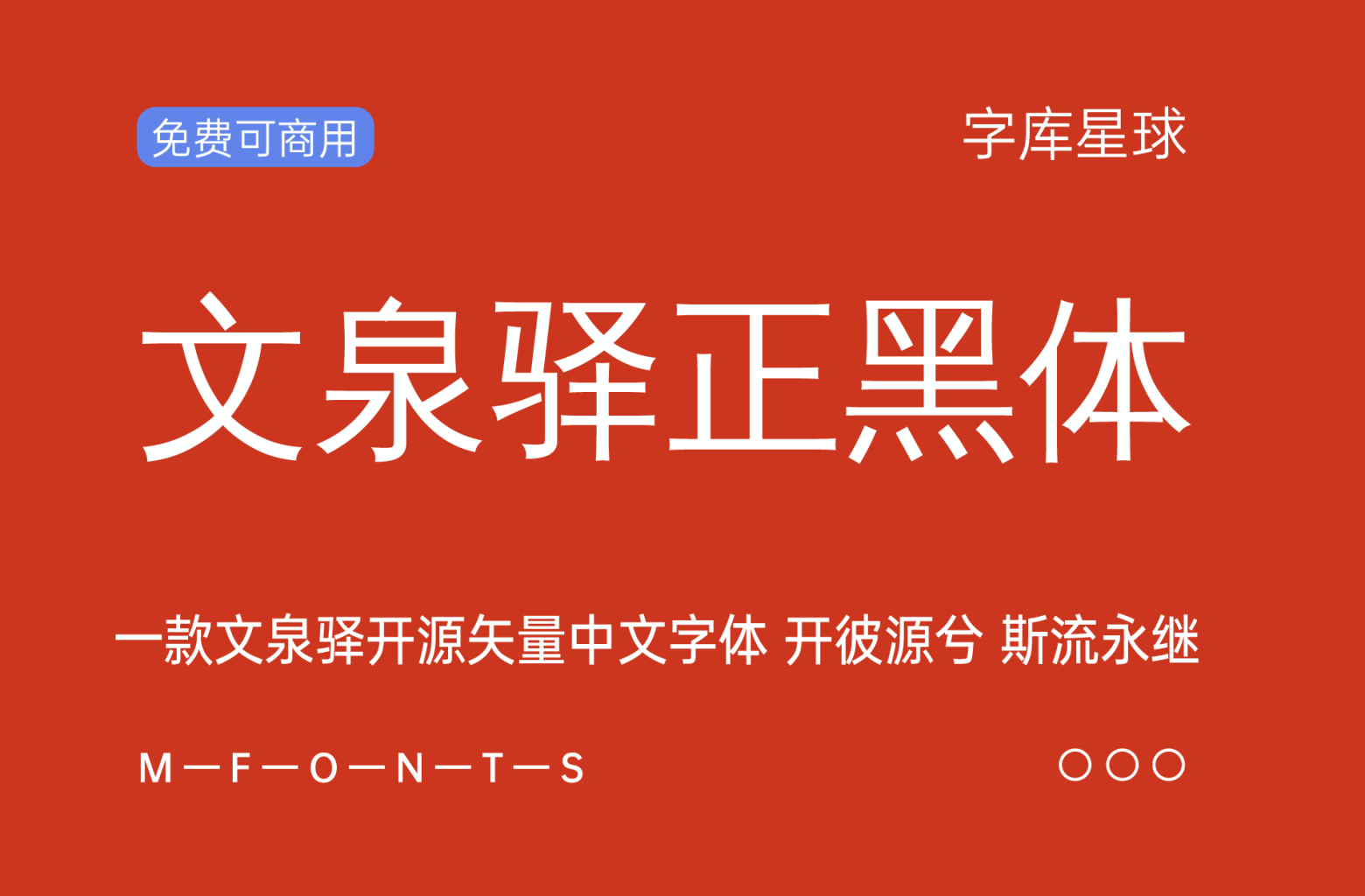
文泉驿正黑体是一个”自由字体“。该字体包含了所有常用简体中文、繁体中文所需要的汉字(最新版本包含超过27842个汉字,完整覆盖GB2312/Big5/GBK以及GB18030标准字符集)。该字体同时还包含了日文、韩文和其他几十种语言符号。除此以外,该字体还嵌入了最新版本的文泉驿点阵宋体的中英文点阵,使得屏幕汉字显示清晰锐利,易于阅读。
作为黑体中文字体,文泉驿正黑为非衬线字体,笔画对比度明显,特别适合屏幕汉字显示以及文档标题字体。